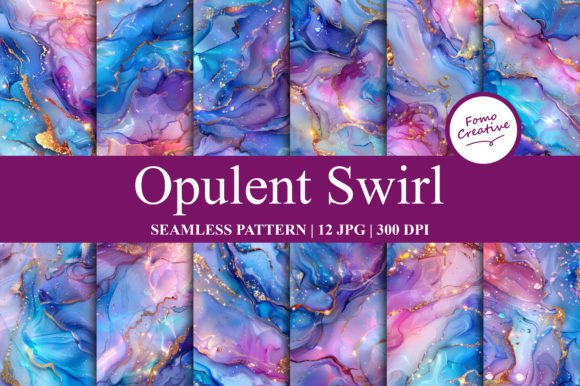
Opulent Swirl
適切なデザイン要素を見つけるのは難しい場合がありますが、Opulent Swirlは作品を即座に引き立てる優れたコレクションを提供します。
POD(オンデマンド印刷)製品、結婚式の招待状、またはソーシャルメディアのグラフィックを作成している場合でも、Opulent Swirlは理想的です。